逐浪古禅素食楷体是由逐浪字库开发的一款瘦长中文字体,这款字体笔触较为详细,字体细长,具有很好的视觉效果。适用于网页设计、平面宣传、艺术设计等等。
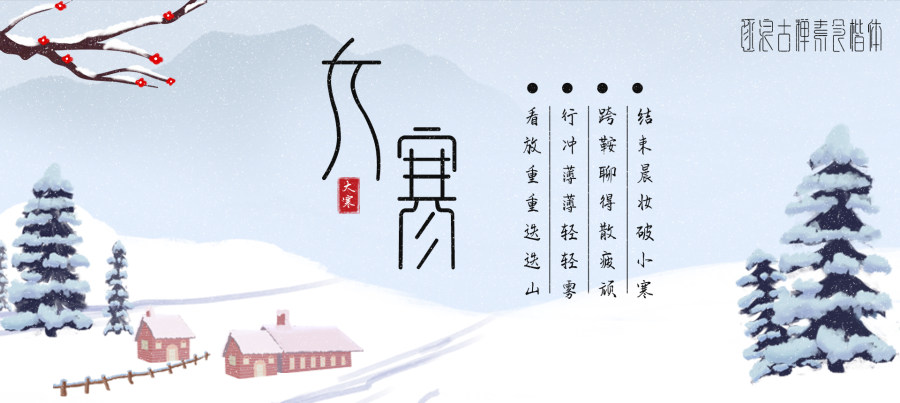
“楚辰体”的字能在轻松时尚的氛围中体现,粗黑为字形基础,不规则的笔画,在排版时能表现跳跃的节奏感。轻快自然的特征能让标题和广告语更加醒目生动。该字体由字体视界对外公开首发,供个人免费商用,企业需付费商用授权使用。